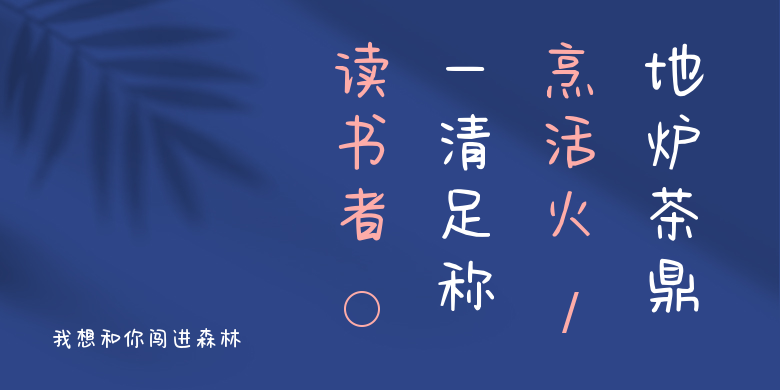
我想和你闯进森林
我想和你闯进森林,这款字体结构工整、笔画清晰,兼顾美观与易读性,适用于标题、正文、海报、包装、LOGO 等多种场景。字形优雅稳定,风格百搭耐看,适配日常排版与创意设计,让文字呈现更舒适、更具质感。我想和你闯进森林一笔一画,皆是细节,以均衡的比例、流畅的线条打造舒适视觉体验,字形端正大气,风格简约现代。无论是商业设计、品牌宣传还是日常排版,都能轻松驾驭,让文字更有格调与力量。我想和你闯进森林字体下载。